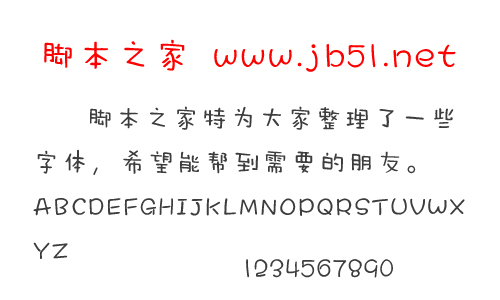
騰祥豆豆體字體風(fēng)格鮮明、特點(diǎn)突出。豆豆體書寫模仿幼兒書寫方式,筆畫隨意放松,富于變化,凸顯稚嫩無(wú)暇,天真童趣的特點(diǎn),。本款字在不影響閱讀的前提下盡顯其特性。本作品可適用于印刷出版兒童讀物、包裝設(shè)計(jì)、廣告設(shè)計(jì)、網(wǎng)頁(yè)設(shè)計(jì)等。歡迎喜歡騰祥豆豆體的朋友前來(lái)下載使用。